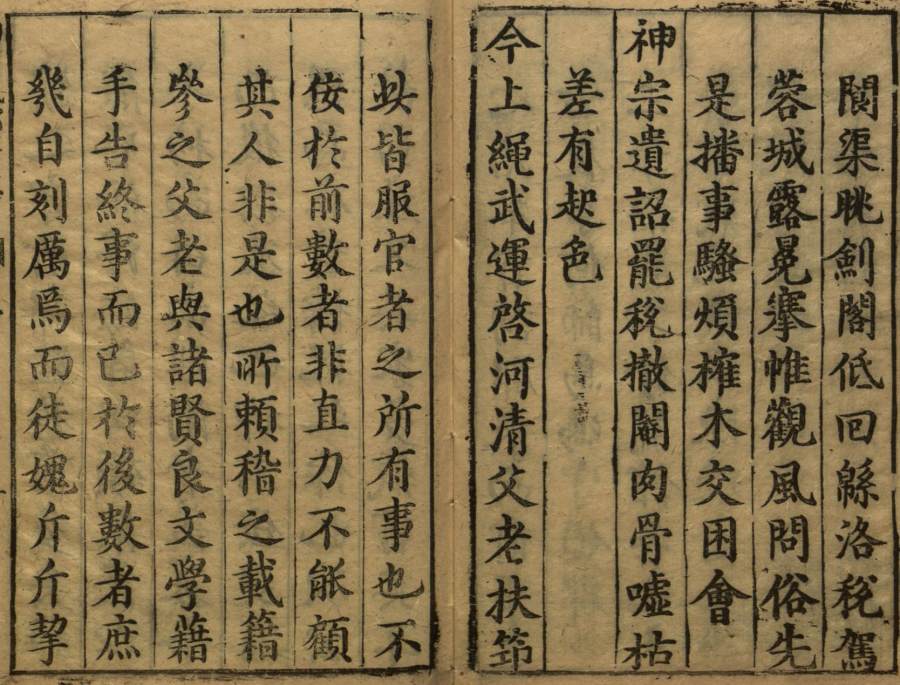
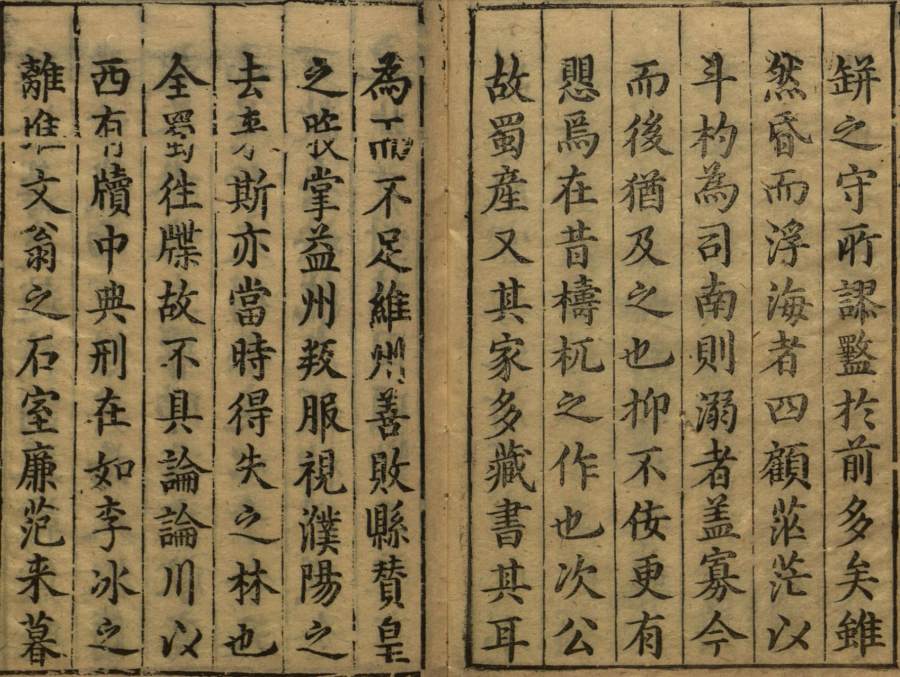
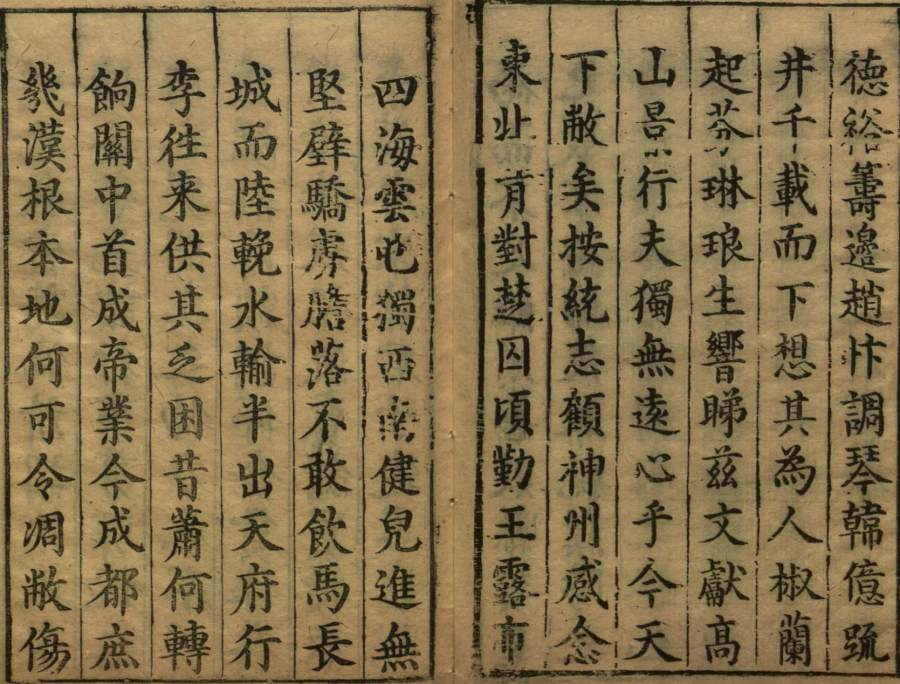
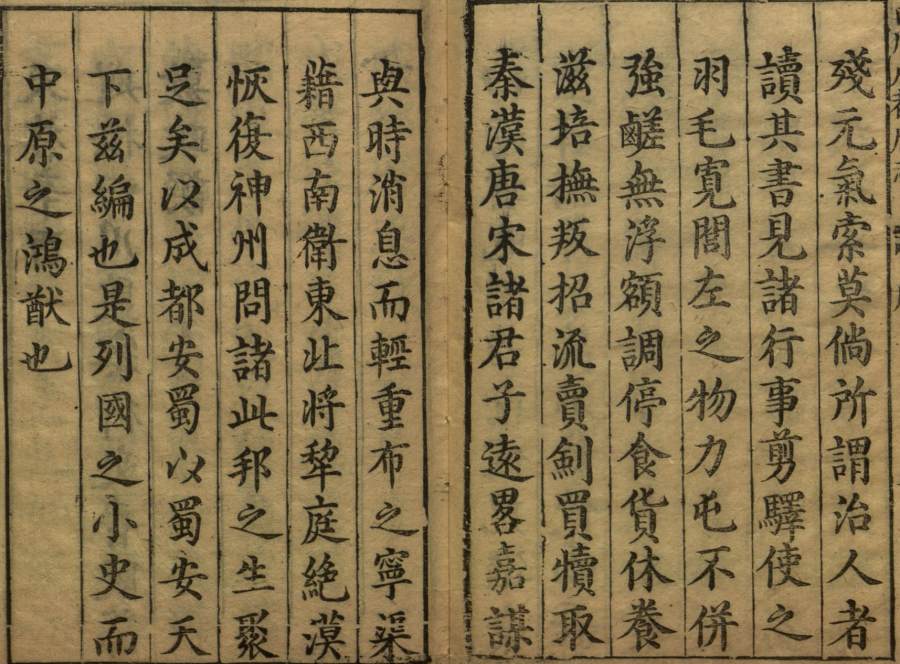
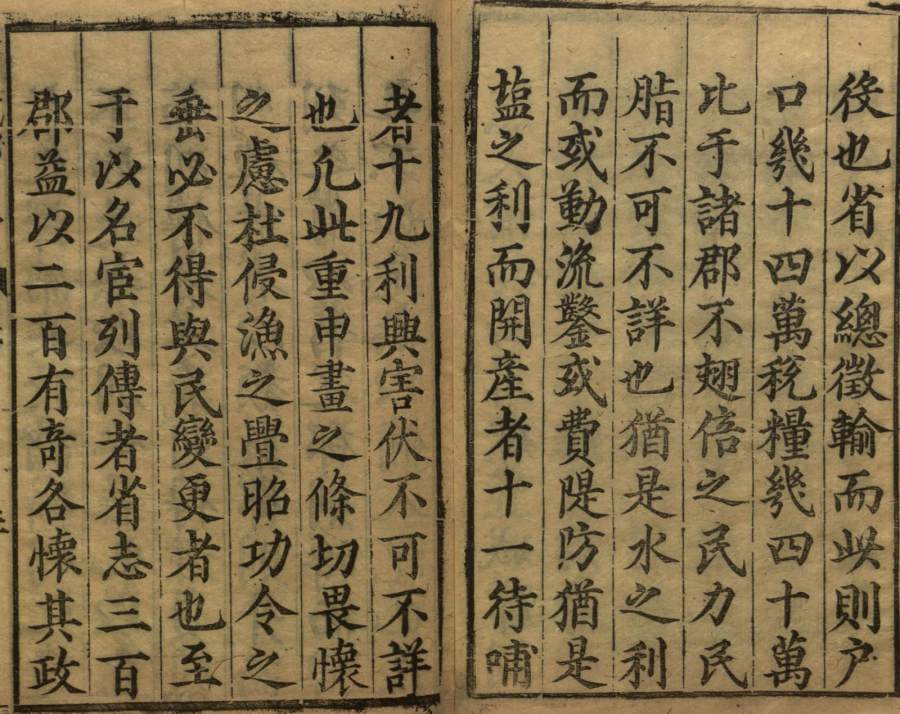
【古迹字体】古籍成都府志原版笔记手迹,字体设计设计参考,字体设计如果在设计字体没有思路的时候,建议多看看这些古代书籍,上面的字体是很有参考价值的。
此《新修成都府志》由明代冯任、张世雍等纂修。全书五十八卷,详细记载了成都府的山川疆域、城池关迹名胜、风俗民情、官守科第、水利盐法、人物艺文志等等。此为此为明天启元年刊本(海内孤本),是目前所能见到的最早一种成都府志
明代纂修成都府志,始于明宣宗宣德初年。这在明天启《成都府志》中有所提及,冯任撰的《成都府志后序》称:“宣庙初,五羊陈公廷器 乃锐为成都府志,亦仅仪禆湛之业。后五十年为成化丙申,襄城李公勉复加纂辑,称全书,而今已放佚不可睹矣。” 陈琏虽有修志之举,然终未竟其事。留待五十年后,即明宪宗成化十二年,李敏 “复加纂辑”。李敏纂修的 “成都府志”(原名《四川成都志》二十五卷),虽称为全书,但经过一百四十五年之后,到明熹宗天启元年,便已 “放佚不可睹”,如今更是片纸无存,莫可稽查了。今可睹者,最早即为明天启初年撰修的府志。
《新修成都府志》是在成化十二年李敏(字公勉)倡导编修的《四川成都府志》基础上编纂的。开局于泰昌元年,以知府冯任等为总裁,谢奇举、张世雍、杨懋方、李莅等进行补充、完善,于万历四十六年成书,天启元年刊印。此书张世雍用力最多。其中以人物和艺文两门所占比重较大。职官、科举、人物共二十三卷;而艺文则多达二十九卷,几乎占全书的一半。字体授权艺文大多取自杨慎等《全蜀艺文志》和杜应芳《续补全艺蜀文志》。舆地部分篇幅虽然不算很大,但对于明代以前成都府所属各州县之山川疆域、城池关津、古迹名胜、风俗民情等记载颇详。而明代成都府所辖地域较广,共领六州二十六县,为清代建制的二倍以上。这对于研究成都古代地域之沿革变迁、名迹风物极有史料价值。